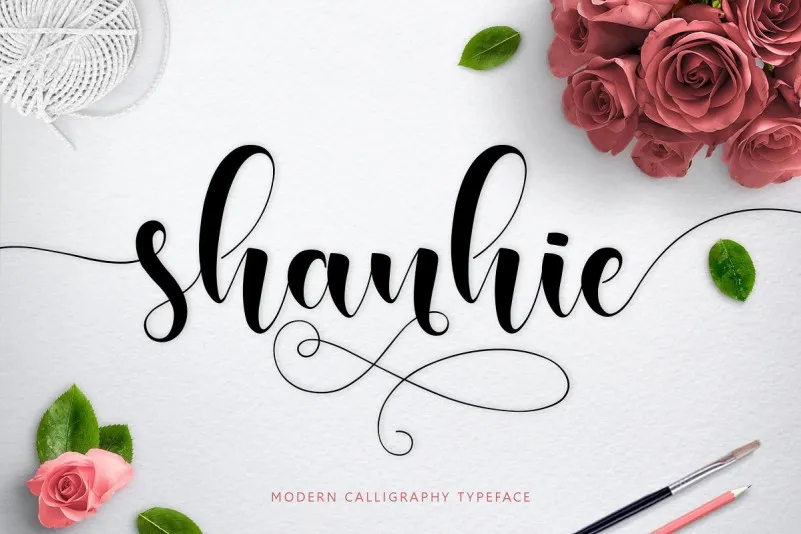
Shanhie Script Font – Download Grátis
Bem-vindo a mais uma página de descobertas do mundo dos fontes! Hoje, apresentamos à vocês Shanhie Calligraphy Font, uma escolha excepcional para aqueles que buscam um toque elegante e moderno em seus projetos design. Especificamente categorizado como fonte script, esta opção é uma mistura perfeita de estilo clássico com um deslizamento único na linha base. Shanhie Calligraphy Font se destaca por seu estilo moderno ao mesmo tempo que manter características originais do calligrafismo. As linhas finas e levemente curvas da fonte fornecem uma elegância natural para qualquer design, tornando-a perfeita para adicionar um toque refinado a anúncios, cartões de convite, materiais de marca, cards de negócios, frases e até mesmo grandes outdoors. Seja em seu próximo projeto criativo ou trabalho profissional, Shanhie Calligraphy Font é uma fonte que se adaptará à sua necessidade. Ela traz um toque especial a qualquer design, tornando-o único e impecável para diversos tipos de aplicação visual.
Designer: m@graphics